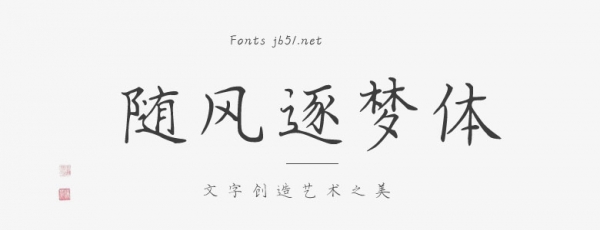
随风逐梦体是一款利落爽快的硬笔手写体,出自于思雨四库的楷体书法字体,给人清新雅致的大方体验,有着极佳的视觉效果。
“每一次与成功的交接,必定是艰苦奋斗的汗水与不甘失败的泪水共同铸就的。我愿做那勇敢的逐梦者,坚定地追寻梦的脚步。”——随风逐梦体。本字库是在国家标准简体字库GB2312所包含6763汉字的基础上,又增加了近200常用字,已经覆盖了大陆99.75%的汉字使用频率,足以满足日常需求。适合应用于艺术设计、平面宣传设计、网页设计,书法字帖等领域。